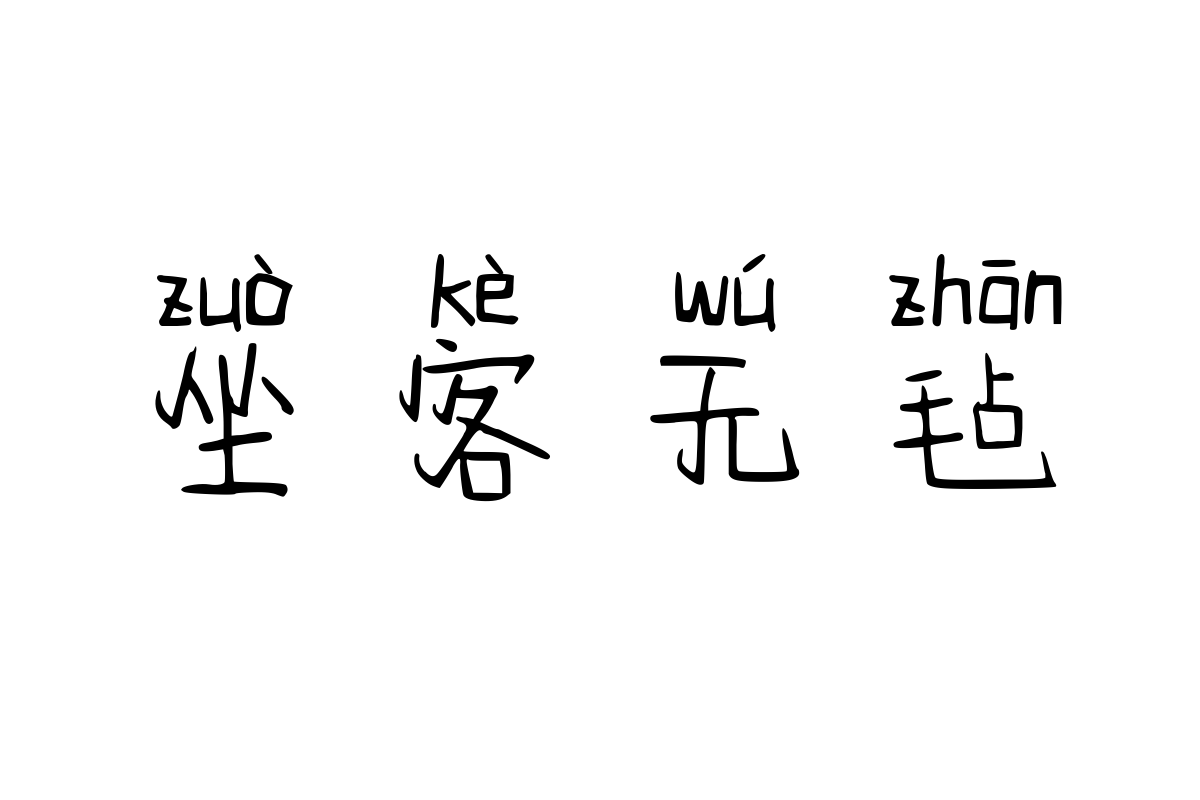
思雨静守从容拼音体是一款由思雨工作室设计的中文字体,具有独特的艺术风格和美感。这款字体以简洁、优雅的线条为基础,通过巧妙的排版和组合,展现出一种宁静、淡定的氛围。它适用于各种设计场景,如海报、宣传册、网页等,能够为作品增添一份独特的艺术气息。
思雨静守从容拼音体的字形特点包括:
1. 线条流畅:字体中的笔画线条清晰流畅,给人一种轻松愉悦的感觉。
2. 结构平衡:字体的结构平衡,各个部分之间的比例协调,使得整体看起来更加和谐。
3. 装饰元素:字体中融入了一些装饰元素,如小圆点、波浪线等,增加了字体的趣味性和艺术性。
4. 文字间距:字体的文字间距适中,既不会显得拥挤,也不会显得空旷,营造出一种舒适的阅读体验。
5. 可读性强:虽然字体较为独特,但仍然保持了较高的可读性,便于读者阅读和识别。
总之,思雨静守从容拼音体是一款具有独特魅力的中文字体,适合用于各种设计场景,为作品增添一份艺术气息。